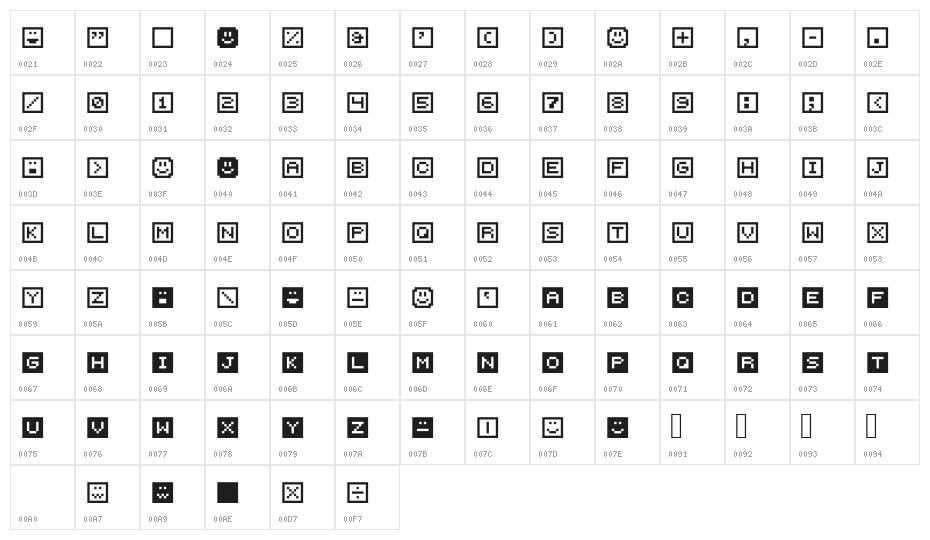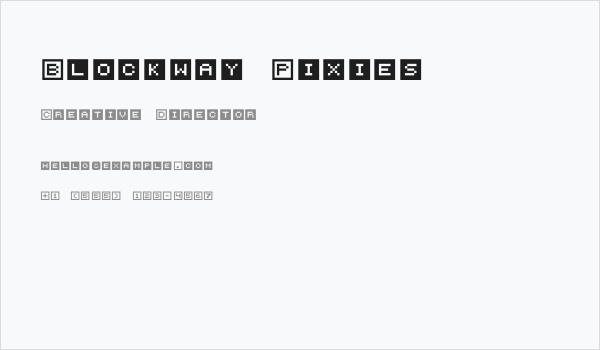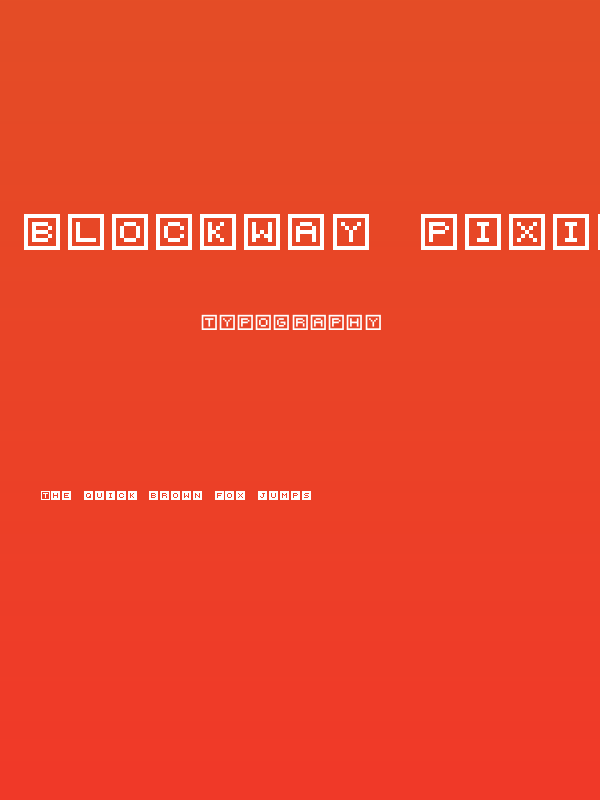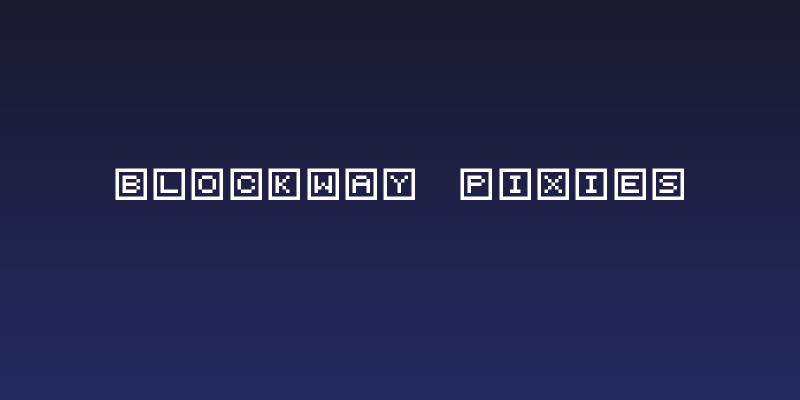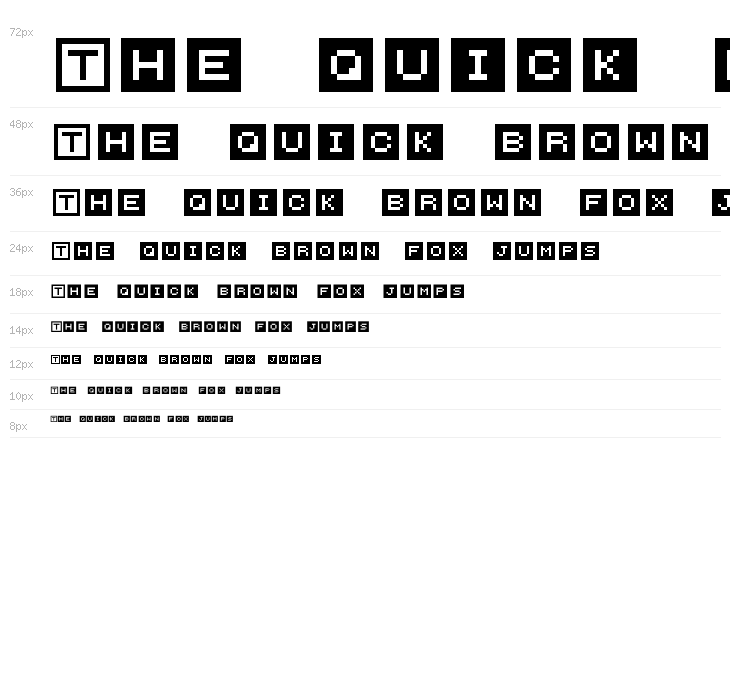
Blockway Pixies Font
BLOCKWAY-PIXIES Groß
BLOCKWAY-PIXIES Kleinbuchstaben
BLOCKWAY-PIXIES Anderer Schreiben
| Kategorien | Pixel |
| Gesamtstil | Vintage |
| Anwendungsfall | Logos, Headlines, Posters |
| Vorgeschlagene Projekte | Ideal for retro video game designs, digital-themed posters, and nostalgic branding projects. |